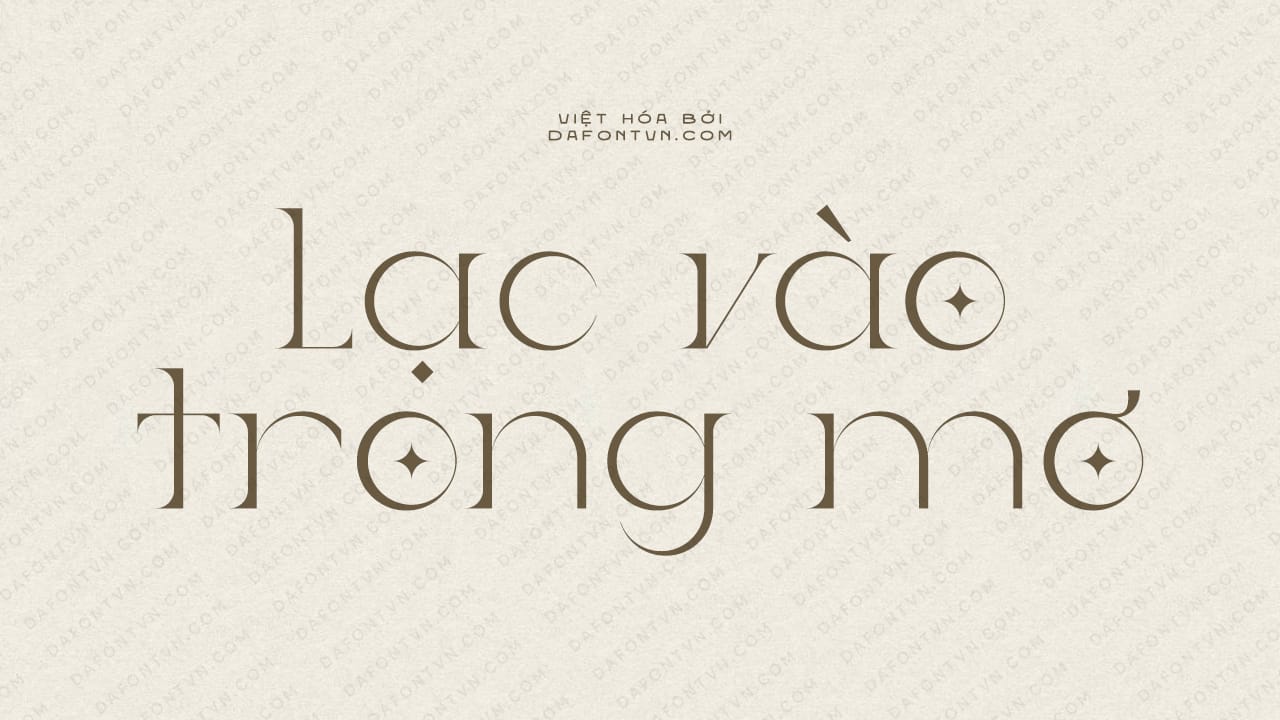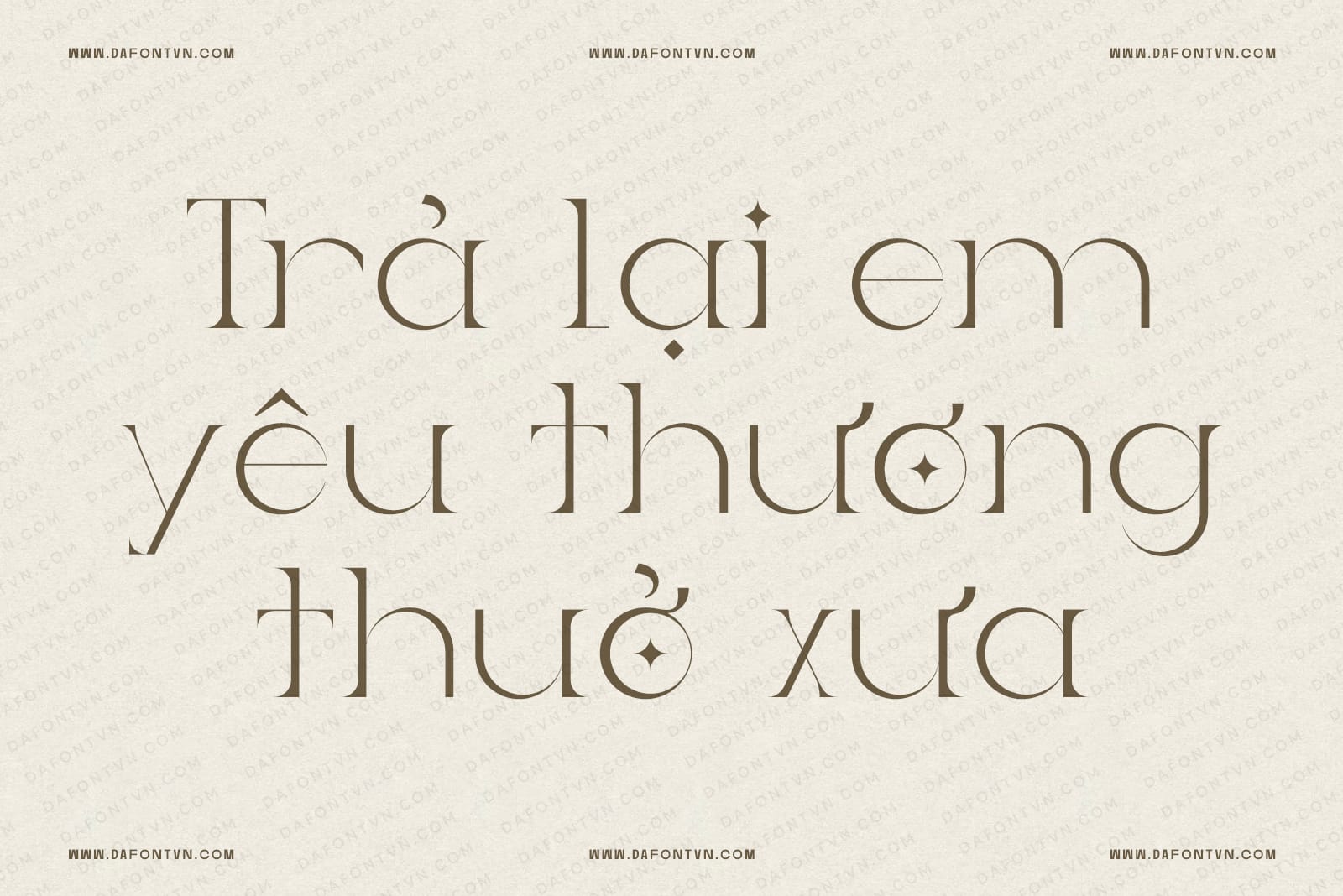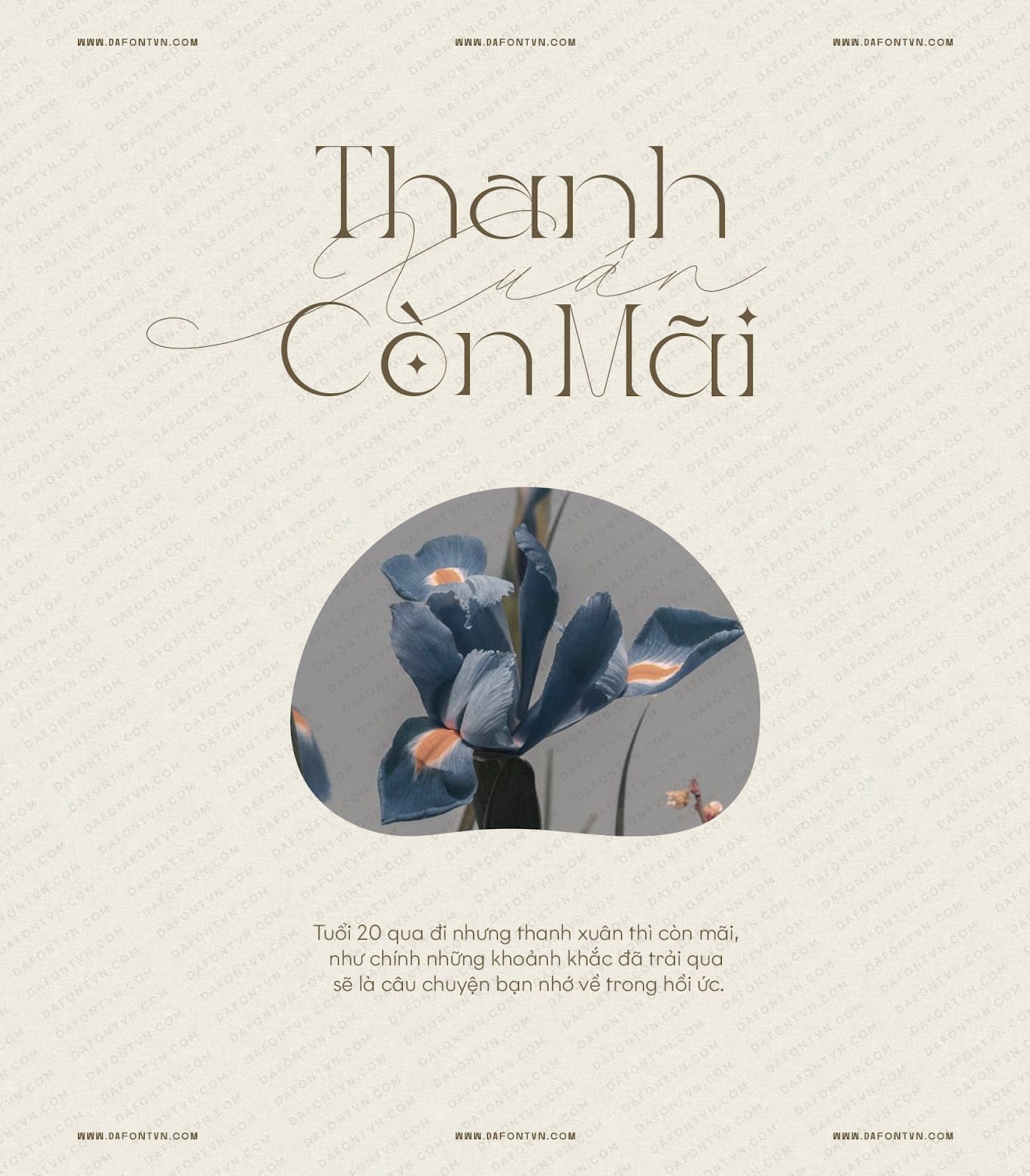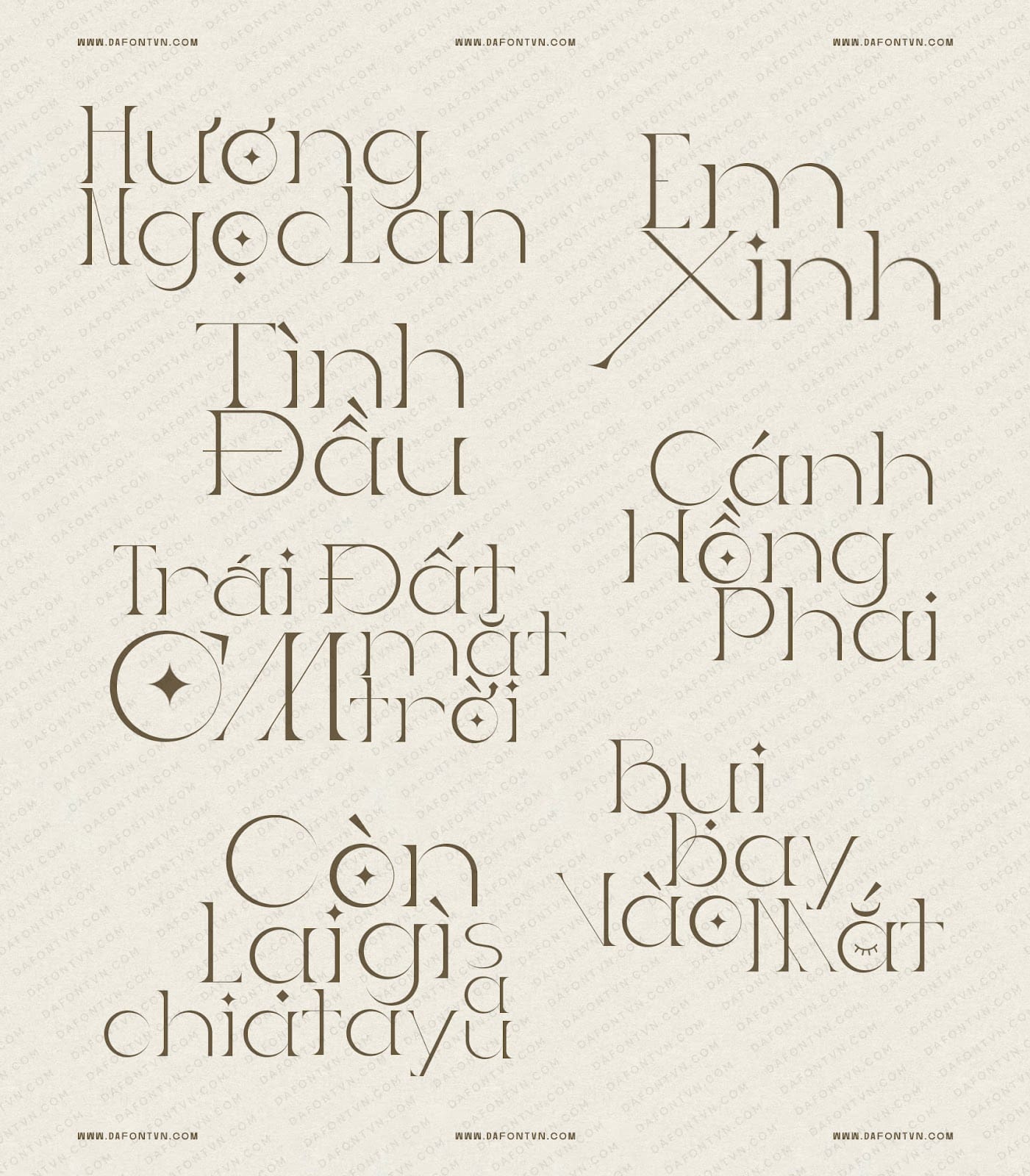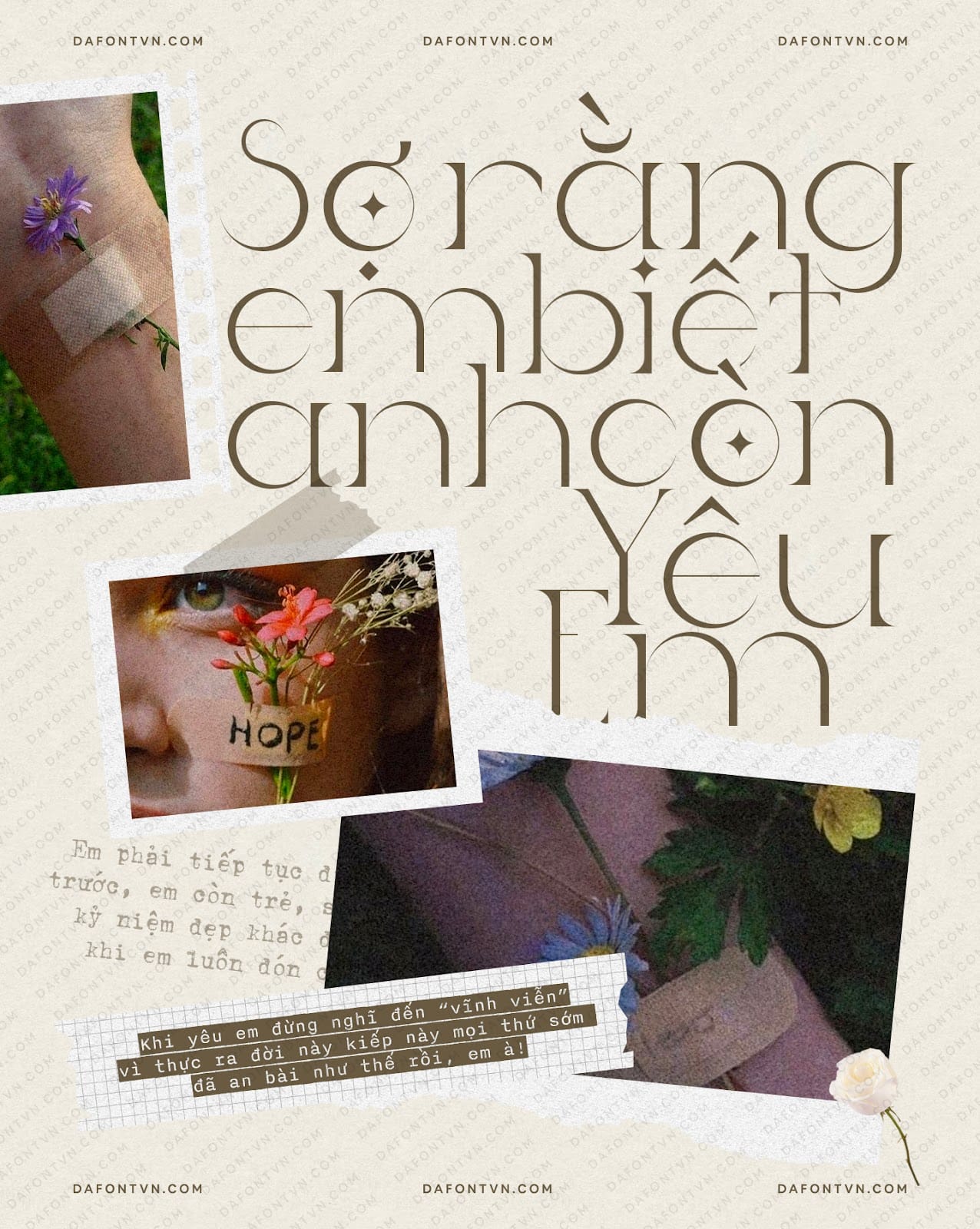
Font Ladybird Light Việt hóa – Sắc nét, tinh tế
Ladybird Light là một font chữ serif tinh tế với các nét sắc như dao cạo với các đường nét cực kỳ tinh xảo để mô phỏng sự sang trọng của Irish Actor, Saoirse Ronan.
Được thiết kế với sự tương phản đẹp mắt và những sự thay thế đầy phong cách, phông chữ Ladybird Light rất ấn tượng. Mỗi glyph đều được thể hiện rõ ràng với sự chú ý đến từng chi tiết; tương phản với bộ chữ thường nhẹ nhàng, tối giản hơn với các ký tự chữ hoa có tính biểu cảm cao, với nhiều lựa chọn thay thế về phong cách, cho phép người dùng tạo ra những thiết kế độc đáo hơn của riêng mình.
Những đường nét tuyệt đẹp của Ladybird với các nét hoàn thiện mềm mại, nhịp nhàng để tạo cảm giác tinh tế vượt thời gian trong khi vẫn sắc nét và hiện đại. Các serif cho phép không gian để hầu hết các nội dung của mẫu chữ, từ đó cho phép chúng chứa đựng những chi tiết phức tạp vô cùng đa dạng trong khi vẫn giữ được sự mượt mà và gắn kết.
Phông chữ này sẽ trông tuyệt vời trong bố cục biên tập tinh tế hoặc để tạo ấn tượng đặc biệt thông qua nhận dạng hình ảnh. Với vô số chữ ghép và phong cách thay thế, bạn sẽ không thể nào cảm thấy nhàm chán với Ladybird Light.
Ngoài ra, Ladybird Light là font chữ được sử dụng làm thumbnail youtube của show Chị đẹp đạp gió rẽ sóng.